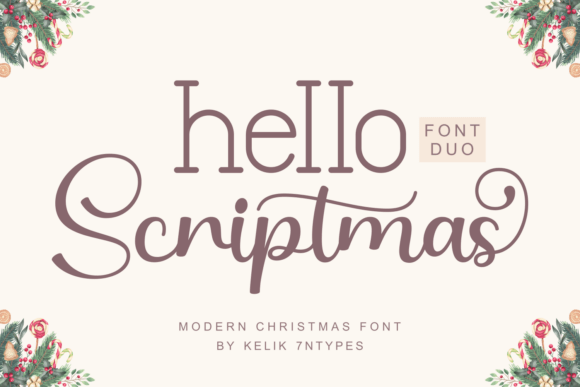
Hello Scriptmas Duo Font
Mencari elemen desain yang tepat bisa jadi sulit, namun Hello Scriptmas Duo Font menawarkan koleksi luar biasa yang akan langsung meningkatkan kualitas karya Anda.
Dibuat dengan presisi, Hello Scriptmas Duo Font menyediakan vektor yang bersih, tipografi yang halus, serta lisensi komersial untuk ketenangan pikiran Anda.
Baik Anda membuat produk POD (Print on Demand), undangan pernikahan, atau grafis media sosial, Hello Scriptmas Duo Font adalah pilihan yang sangat ideal.